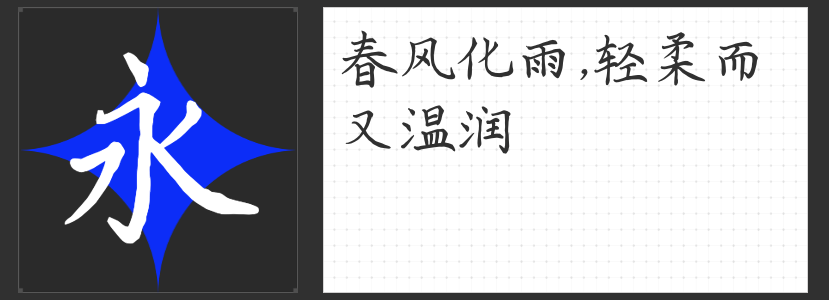
四款书法字体推荐:让设计绽放东方韵味的艺术之选
书法字体以其独特的笔触韵律与文化底蕴,成为设计中传递情感、塑造意境的重要元素。无论是品牌标识、文化海报,还是书籍装帧、艺术创作,一款契合主题的书法字体都能为作品注入灵魂。以下四款书法字体,各具风格,或优雅隽永,或洒脱奔放,为设计师提供丰富的创意表达空间。
一、创客贴杨莹凤卿体
杨莹凤卿体以“优雅有力”为核心特质,字形结构严谨规范,笔画起收分明,既保留传统书法的骨力,又融入现代设计的简洁美感。其笔触流畅而不失力度,转折处圆润自然,整体风格端庄大气,尤其适合字帖临摹、儿童读物等需要清晰辨识与审美引导的场景。这款字体在标准字形的基础上,通过细微的笔锋变化传递书写者的情感,使文字兼具实用性与艺术性,为设计增添一份温润的东方气质。
二、励字舒体简繁
励字舒体简繁以“师古而不泥古”为设计理念,将楷书的端庄、行书的流畅、隶书的古朴、草书的奔放与篆书的浑厚融为一体,形成独特的复合风格。其字形飘洒圆秀,笔势沉雄峭拔,既有壮士筋骨涌现的刚劲,又含逸气恣肆的灵动。在结构上,它巧妙平衡各书体特征,避免单一风格的单调;在风格上,取颜真卿的雄浑与柳公权的清劲,形成刚柔并济的视觉张力,适合需要表达文化深度与艺术张力的设计场景。
三、高手字斋树高行书
字斋树高行书以“连贯流畅”为显著特点,笔画之间自然衔接,如行云流水般一气呵成。其笔触轻重缓急有序,提按分明,既保留行书的洒脱,又通过结构优化提升可读性。这款字体适合需要传递动态感与节奏感的设计,如品牌标语、文化海报等,能以文字的韵律引导观者的视线,营造出灵动而富有生命力的视觉体验。
四、高手兵克行江湖
高手兵克行江湖以“浑厚洒脱”为核心风格,笔画落笔有力,收放自如,笔力劲健而不失灵动。其字形结构疏密有致,既有草书的奔放,又含楷书的稳健,形成独特的“刚柔并济”美学。这款字体适合需要表达力量感与自由精神的设计,如运动品牌、武侠文化主题等,能以文字的张力传递品牌的个性与态度。
书法字体的魅力,在于它不仅是文字的载体,更是情感的延伸与文化的符号。这四款字体各具特色,或优雅、或奔放、或灵动、或浑厚,为设计师提供了丰富的表达工具。无论追求传统韵味还是现代创新,它们都能以独特的笔触语言,为设计注入东方美学的灵魂。